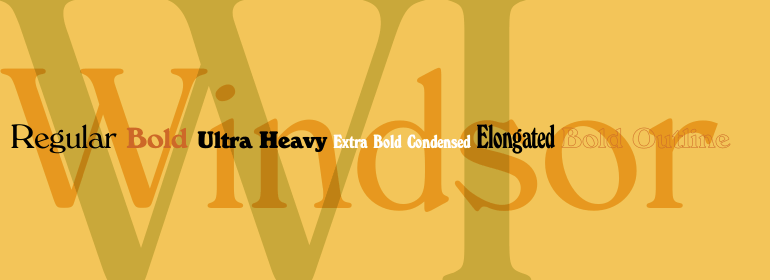
Windsor™
Windsor™,这款字体结构工整、笔画清晰,兼顾美观与易读性,适用于标题、正文、海报、包装、LOGO 等多种场景。字形优雅稳定,风格百搭耐看,适配日常排版与创意设计,让文字呈现更舒适、更具质感。Windsor™一笔一画,皆是细节,以均衡的比例、流畅的线条打造舒适视觉体验,字形端正大气,风格简约现代。无论是商业设计、品牌宣传还是日常排版,都能轻松驾驭,让文字更有格调与力量。Windsor™字体下载。
Eleisha Pechy, who designed typefaces around 1900 for the British type foundry Stephenson Blake, created the initial Windsor family. This family of typefaces, which has since been subsequently digitized, is available from Linotype in six different weights: Light, Bold, Ultra Heavy, Extra Bold Condensed, Elongated, and Bold Outline. Typefaces like Windsor were used extensively at the turn of the century in advertising on both sides of the Atlantic. The letterforms have an antiquated feel to them; their proportions seem slightly inspired by the art nouveau movements that were abounding during the time of their conception.
Windsor Extra Bold Condensed and Windsor Elongated are both superb examples of condensed serif display faces. Their ovular forms both appear somewhat egg like. Windsor Ultra Heavy bears similarities to Cooper Black , a more modern, American style typeface that was created 20 years later."